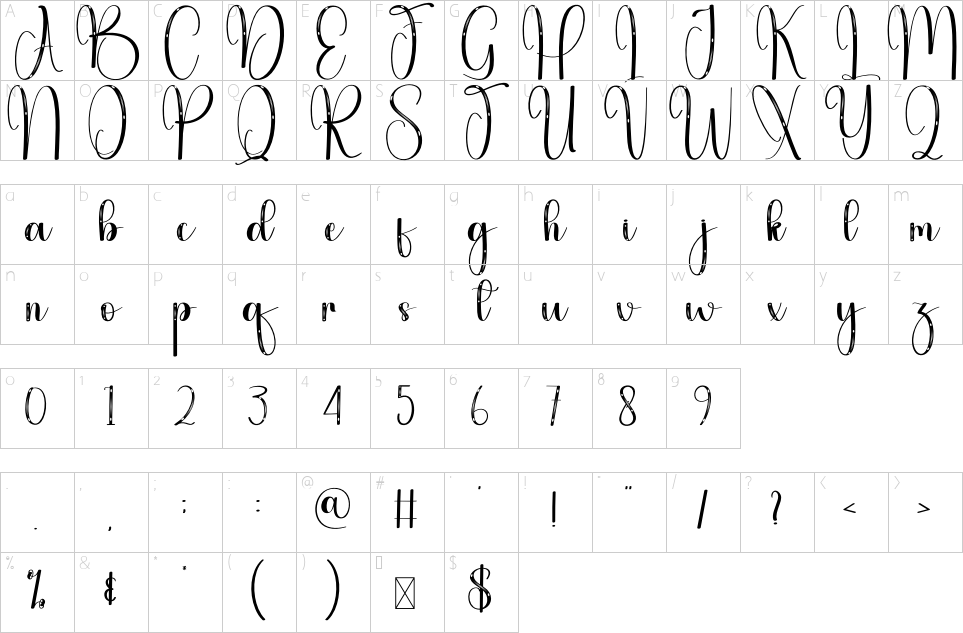
Anthem Font – Fonte Grátis
Anthem Font
A fonte gratuita Anthem é uma escolha ideal para designers que buscam um estilo moderno e elegante. Desenvolvida por William Jhordy, Anthem oferece uma variedade de linhas com um design fluido e sofisticado, adequado para criar textos com um toque de exclusividade. Esta font é especialmente atraente para aplicativos de design gráfico, projetos de blog ou qualquer projeto onde você deseja adicionar um toque atraente aos seus documentos. Com downloads já totalizando 312 vezes, Anthem provou sua capacidade de se adaptar a diferentes ambientes e estilos, tornando-se uma opção confiável e versátil para os designers digitais. Sua simplicidade e elegância fazem da Anthem uma fonte gratuita que merece ser explorada.
Mapa de caracteres da fonte Anthem Font